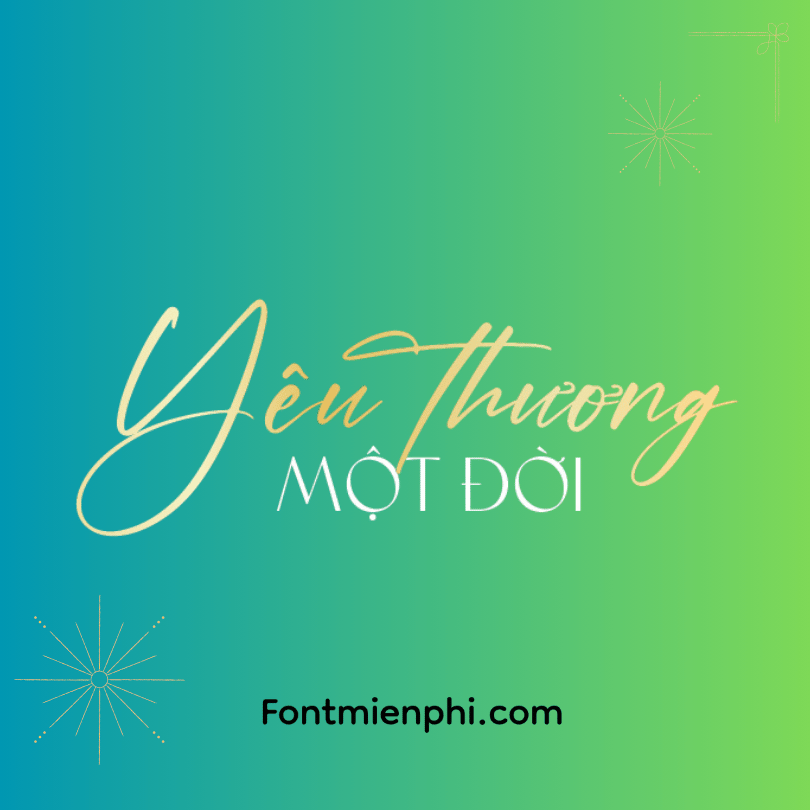
Font Việt hóa 1FTV VIP Tropical Qebalon Serif
Font Việt Hóa 1FTV VIP Tropical Qebalon Serif – Phong Cách Nhiệt Đới Tinh Tế
Font 1FTV VIP Tropical Qebalon Serif là bộ font chữ Việt hóa cao cấp, lấy cảm hứng từ phong cách nhiệt đới pha trộn nét hiện đại, phù hợp cho thiết kế sang trọng, thời trang, du lịch, ẩm thực và thương hiệu cao cấp. Với kiểu chữ serif thanh lịch, đường nét mềm mại nhưng vẫn giữ nét cổ điển, font này giúp tạo điểm nhấn đẳng cấp cho logo, poster, menu nhà hàng và các ấn phẩm quảng cáo.
Đặc điểm nổi bật:
✔ Hỗ trợ full bộ Tiếng Việt (TV) – Đảm bảo rõ ràng, mượt mà khi sử dụng.
✔ Phong cách nhiệt đới pha lẫn hiện đại – Phù hợp ngành thời trang, resort, F&B.
✔ Đa dạng kiểu chữ – Đầy đủ các phiên bản Bold, Italic, Regular linh hoạt trong thiết kế.